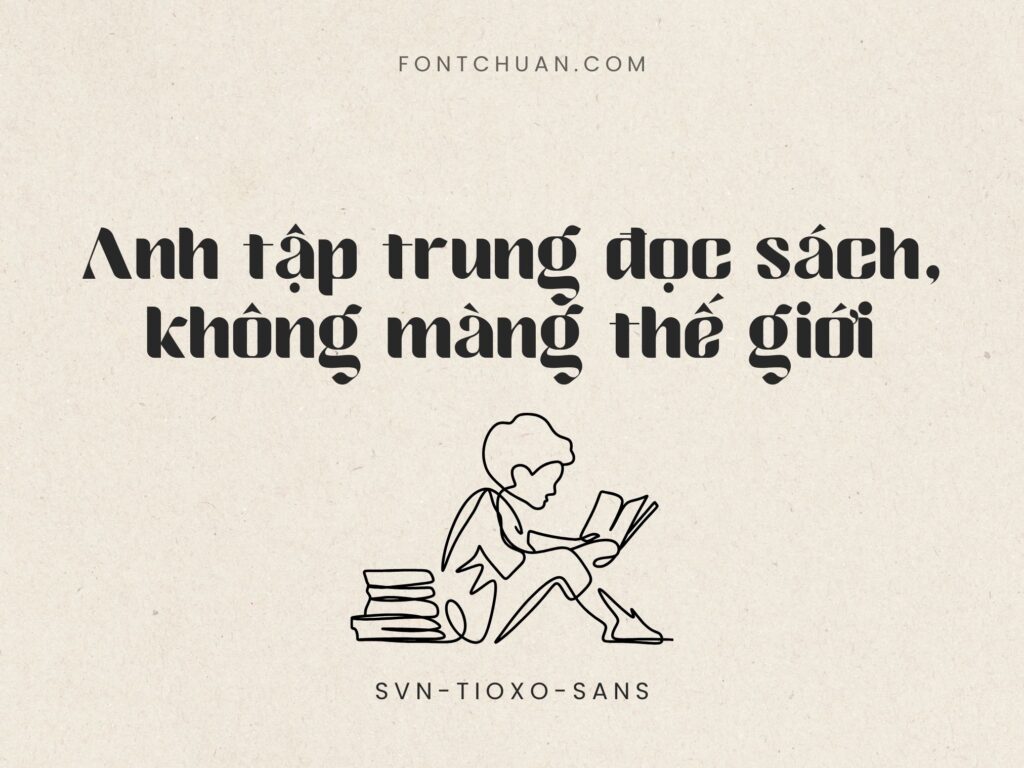
Font SVN Tioxo Sans là phiên bản Việt hóa của kiểu chữ Tioxo Sans, được thực hiện bởi STYLEno.1 Fonts. Tioxo Sans là một kiểu chữ hiển thị với một trọng số duy nhất, được thiết kế bởi FO DA. Font này lý tưởng cho các thiết kế quảng cáo, bao bì sản phẩm, các dịp lễ hội và biên tập. Với thiết kế hiện đại và độc đáo, Tioxo Sans mang đến sự mới mẻ và sáng tạo cho các dự án thiết kế.
SVN Tioxo Sans phù hợp cho các dự án thiết kế yêu cầu sự nổi bật và hiện đại, như thiết kế logo, tiêu đề, bao bì sản phẩm và các ấn phẩm quảng cáo. Các ngành nghề như quảng cáo, công nghệ và giáo dục có thể tận dụng font này để tạo điểm nhấn trong thiết kế. Ngoài ra, font cũng phù hợp cho các sự kiện như Tết, Giáng sinh, Valentine và các lễ hội khác.